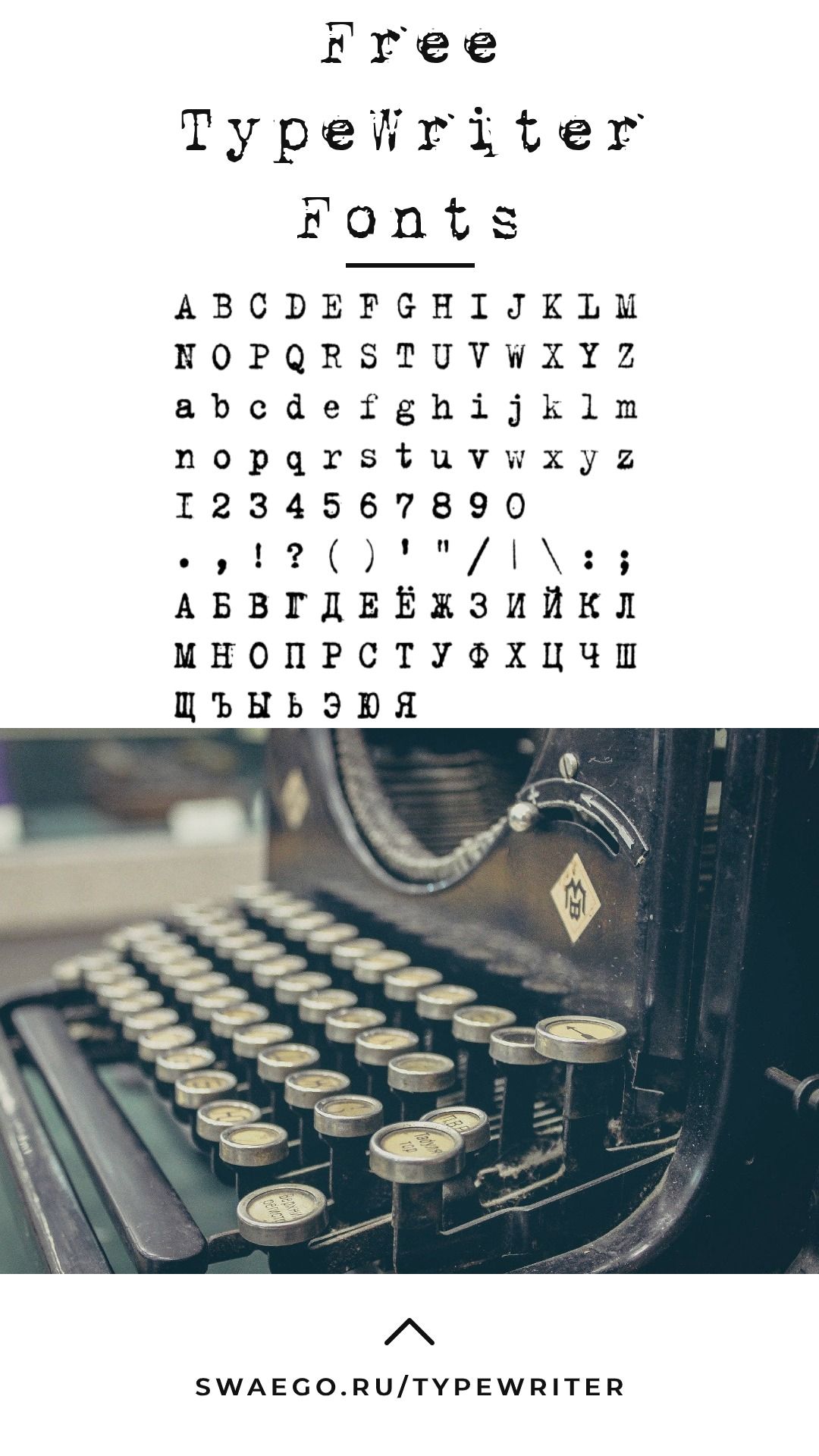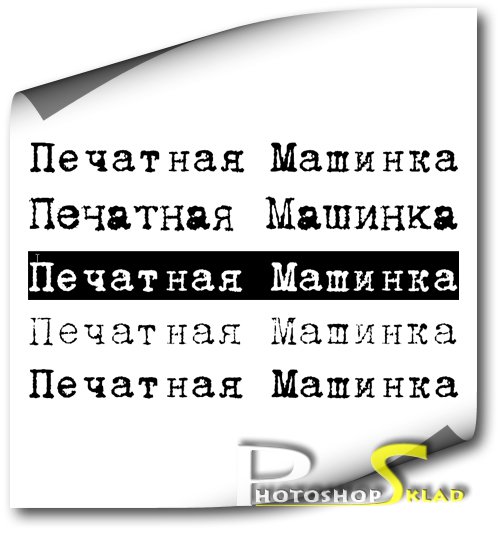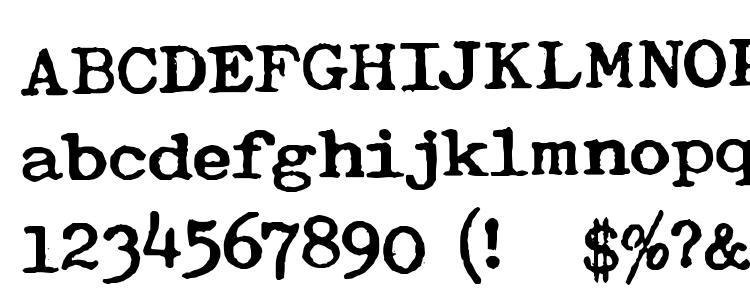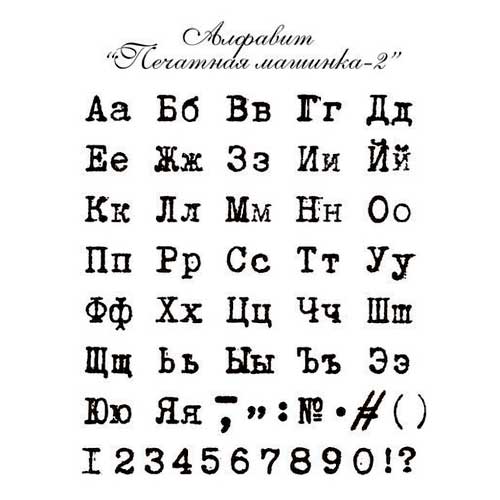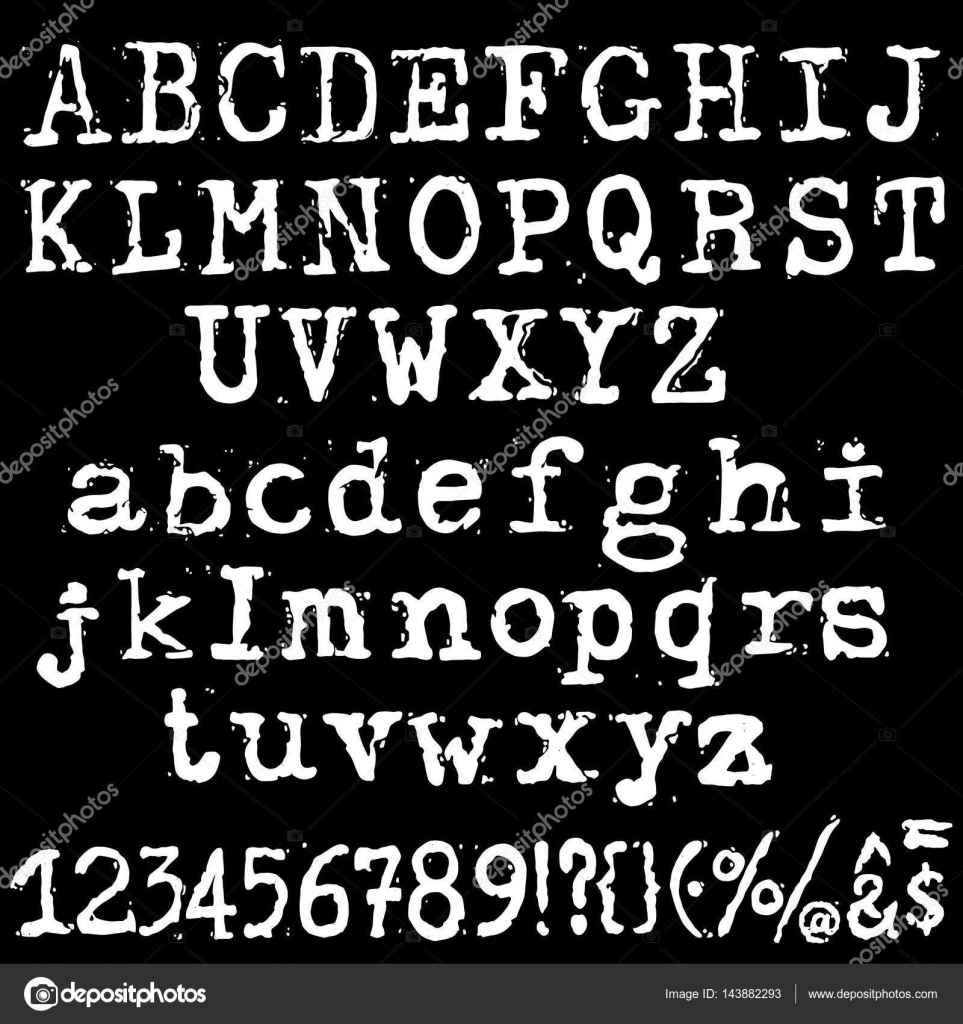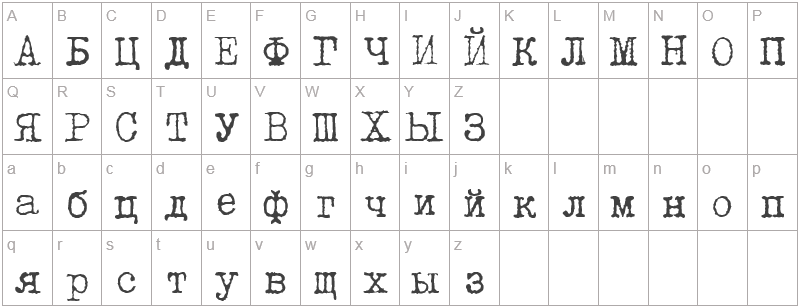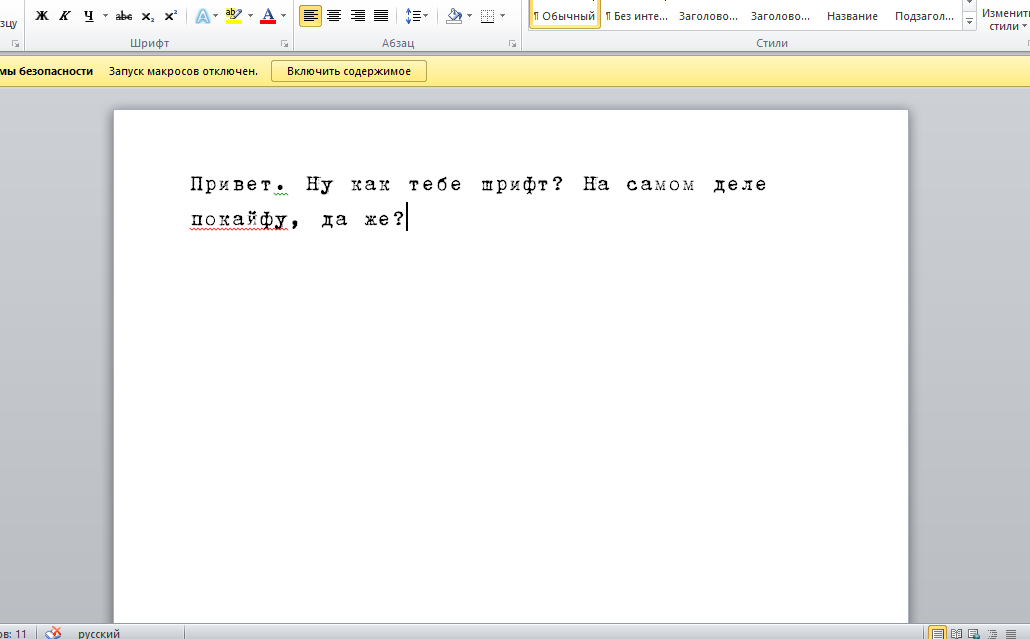
Название сегодняшних материалов в подборке полностью определяется способом их создания — это шрифты печатной машинкой. Теоретически, по форме и стилистике они должны соответствовать реально напечатанным текстам. Похожий принцип типографики встречался в заметках про граффити или надписи мелом на доске — по данным наименованиям вы сразу четко представляете их внешний вид.
Если говорить о визуальной составляющей, то тут все достаточно тривиально. В целом нет такого разнообразия как в декоративных и оригинальных шрифтах. Варианты отличаются разве что качеством / силой «оттиска» для букв и наличием неких посторонних «вкраплений»: где-то текст получается более четкий, в других случаях он выглядит слабо пропечатанным.
Brother Deluxe 1350
1942 Report
Urania Czech Font
My Underwood Font
Tox Typewriter
Through the Night
Typical Writer Font
Kingthings Typewriter
Traveling Typewriter
Rough Typewriter
CarbonType
Harting
Secret Typewriter
Courier Prime
DK Trashtype Font
Love Letter TW
AFL Font Pespaye Nonmetric
Veteran Typewriter
Есть варианты машинописных шрифтов, которые имеют чуть больше декоративных элементов. В принципе, по некоторым заметно, что они не напечатаны, но все же при этом несут в себе схожую интересную стилистику.
NelsonOldNewsPaper Font
Telegraphem
Old printing press
Subway Novella
Punkbabe
Xerography Font
F25 Blackletter Typewriter
Type Keys
Русские печатные шрифты
Дополнительно нашли немного кириллических фонтов для рунета.
К сожалению, оригинальных картинок с их применением здесь не так много, поэтому размещаем скриншоты с доступными символами алфавита — это даст понимание используемого в них стиля. Очевидно, что машинописных шрифтов на русском гораздо меньше англоязычных, но с десяток точно наберется.
TrixieCyr Plain
Bezpredmetizm
DS Moster
B52
a_OldTyperNr Regular
DS VTCorona Cyr
ABC_TypeWriterRussian
Lettera Trentadue
TypeWriter Normal
Prestige-Normal Regular
Vector Old Typewriter Font
Vintage Grunge Typewriter Letters
Alphabet 5 Variations of Every Letter
Typewriter Text on an Aged Paper
Type Writer Alphabet Handmade Letters
Vector Old Typewriter Font
Font Printed on Vintage Typewriter
ABCD Letters Written with a Typewriter
Truetypewriter PolyglOTT шрифт
Truetypewriter PolyglOTT
Обычный
Truetypewriter PolyglOTT
Компьютерный шрифт Truetypewriter PolyglOTT разработан для имитации текста, напечатанного на стандартной печатной машинке.
В отличие от других существующих аналогичных шрифтов, Truetypewriter PolyglOTT создавался не как декоративный шрифт, имитирующий «старую», «разбитую», «грязную» и т.п. машинку, но и не как идеально правильный типографский шрифт: целью создания Truetypewriter PolyglOTT было достижение максимальной реалистичности отображаемого текста — как при печати, так и на экране монитора. Кроме того, Truetypewriter PolyglOTT имеет многоязычную поддержку и включает в том числе множество архаичных символов, позволяя, таким образом, печатать тексты даже на тех языках, для которых печатных машинок никогда не существовало.
Все символы, включённые в данный шрифт, либо (в большинстве случаев) полностью сделаны вручную, либо основаны на отсканированных изображениях отпечатанных на машинке букв, но при этом все они внимательно отредактированы вручную для достижения разумного компромисса между высокой детализацией символов и минимизацией количества контрольных точек, составляющих контуры символов, что позволило добиться относительно небольшого размера файла шрифта при сохранении достаточно высокой детализации.